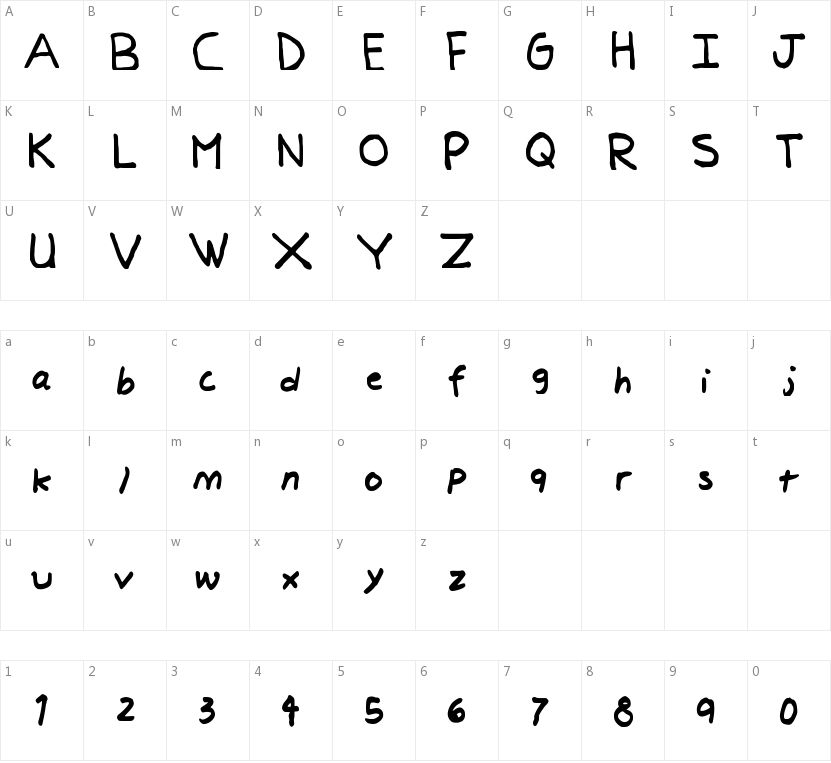
Elementary, My dear
"Elementary, My dear" 字体是一种免费的手写风格字体,适用于各种设计和排版应用,例如海报、卡片、标志等。它的特点是清晰易读、流畅自然,仿佛是以钢笔或毛笔书写而成。此字体具有多种不同的字母形状,包括粗体、斜体、直立体等,可以满足不同排版需求。此外,该字体还包括了多种标点符号和特殊字符,如问号、感叹号、括号等等。总之,如果你正在寻找一种清新自然、可读性高的手写字体,"Elementary, My dear" 可能是你的不错选择。
Elementary, My dear是一款非常不错的手写艺术字体,具有很好的视觉感,适合于文化类的宣传设计、商业类品牌的广告和产品包装设计以及个性化文字排版等较多场景。
Elementary, My dear字符映射图